Cet ouvrage revient d’abord sur l’apparition des écritures dites inclusives et non-binaires, pour esquisser les prémices d’une approche post‑binaire de la typographie. En rappelant la portée politique du dessin de caractères, Camille Circlude montre comment le champ du design typographique offre désormais un espace inédit permettant à l’écriture d’embrasser le vaste prisme des genres, au-delà de la binarité.
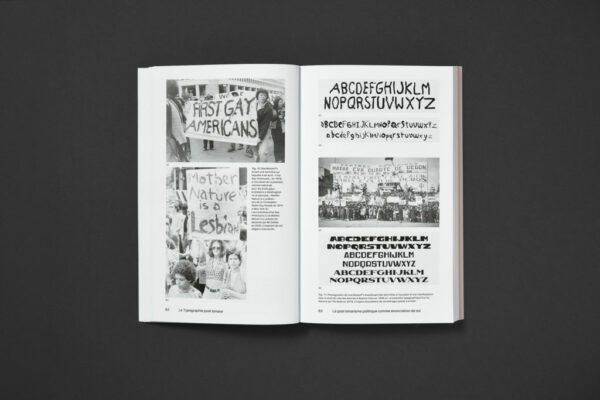
La typographie est ainsi appréhendée comme une technologie émancipatrice permettant de résister à l’hégémonie et d’habiter l’hybridation des formes. Elle offre aujourd’hui la possibilité de matérialiser les existences queers, non-binaires, genderfluid, agenres et genderfuck dans ces espaces partagés et symboliques que sont la langue et l’écriture. En mobilisant le concept de post-binarisme politique, l’auteur·ice, membre fondateur·ice de la collective Bye Bye Binary, invite à adopter un positionnement politique permettant l’affirmation de nouvelles énonciations de soi. Camille Circlude dresse ici un état des lieux de six années d’expérimentations (2017-2023) d’une pratique qui ne cesse de se propager, et qui continue de s’écrire au présent.